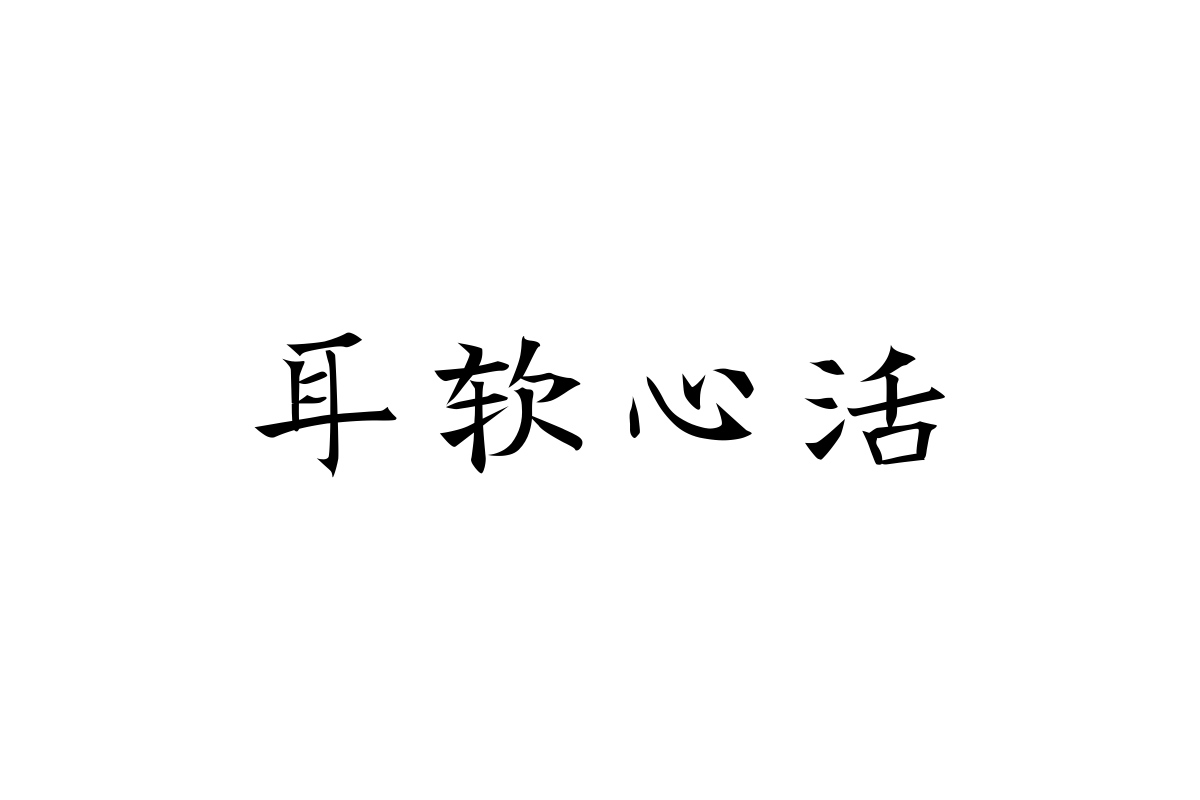
汉仪新蒂苏孝慈碑字体是根据1888年在中国陕西出土的苏孝慈墓碑铭文设计的。书法风格呈现出南北朝时期到唐朝书法的过度,从中可以窥探唐朝楷书的一些风格。
该字体书写结构严谨、运笔纯熟,繁体和简体均很好地保留了苏孝慈墓碑铭文内敛庄重的气质。因此,汉仪新蒂苏孝慈碑是一款具有独特风格和特点的商用字体,适用于需要展现传统文化和艺术气息的商业项目。